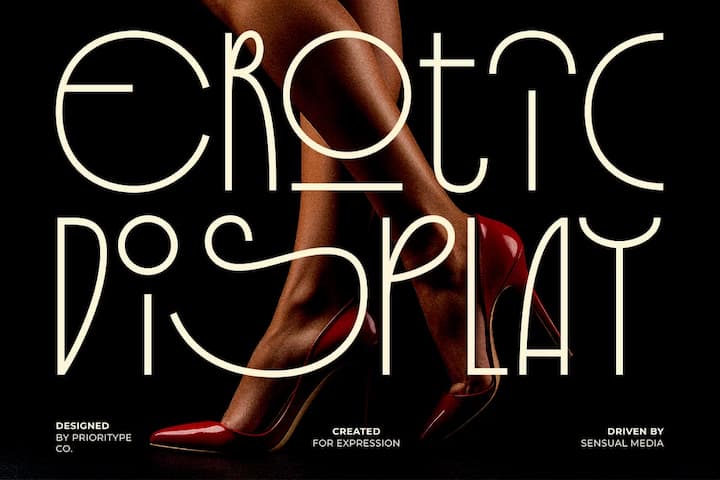
Erotic Display
これでもかというぐらいギリギリまで攻めた変形ディスプレイ。グリフがこれ以上やられたら何の文字か分からなくなるほどにまで崩されているかなり大胆な書体で、形の面白さが最優先。もう可読性はまったく無視である(笑)。ライトウェイトのモノラインなので、それで雰囲気がややシックに保たれているだろうか。ポスターなどにズガンと使うと効果的だろうけど、ちゃんと読めるコピーは別に必要かも。1ウェイトのみ。